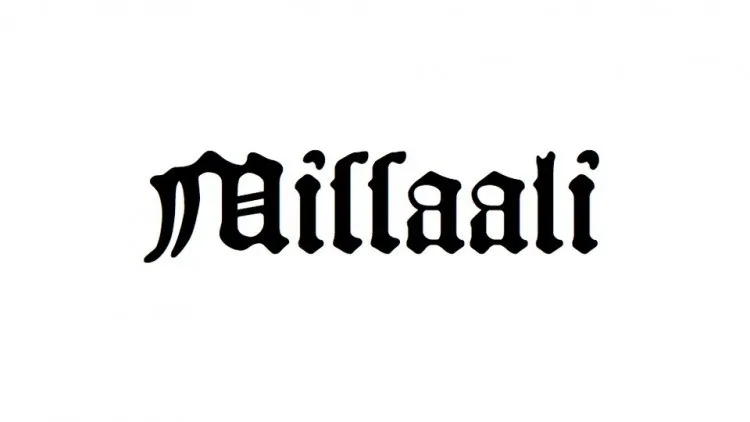
Missaali é uma elegante e sofisticada fonte de display, criada pelo famoso designer de fontes Tommi Syrjänen, inspirada no estilo gótico fraktur. Originária do Textura germânico utilizado pelos impressores barbados Ghotan para publicar missais e salteros na década de 1480s. Misturar modernidade com uma elegância medieval, Missaali é perfeito para aplicações visuais que buscam dar um toque único a qualquer design. Com sua tipografia arquitetônica e detalhes impressionantes, essa fonte será a escolha certa para projetos que exigem destaque visual. Suavemente escrita, mas ainda assim de grande impacto, Missaali é ideal para gráficos digitais e materiais impressos. Seja para criar um design web moderno e dinâmico, ou dar vida aos elementos do seu site pessoal em uma estética clássica e sofisticada, esta fonte está aqui para fazer a diferença. Não apenas uma fonte de display, mas uma parte essencial de qualquer estratégia visual que busque se destacar.